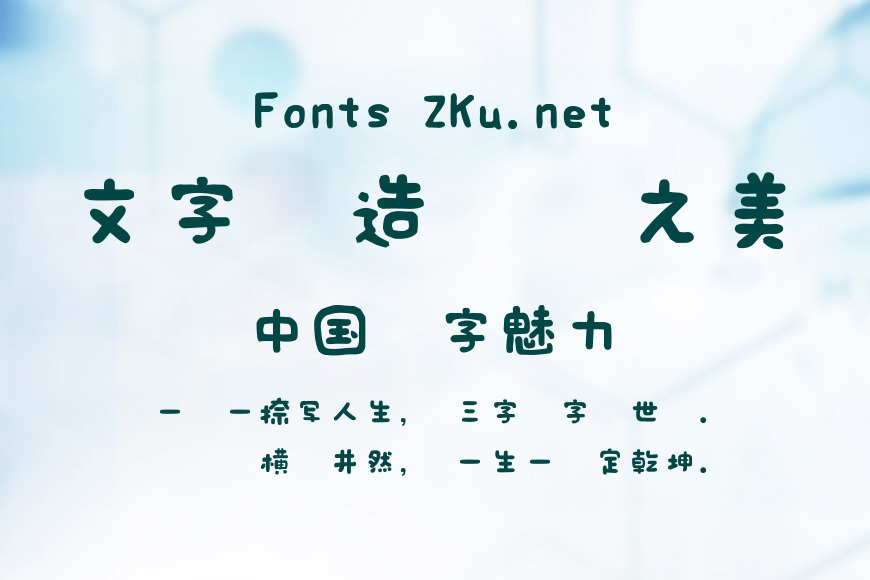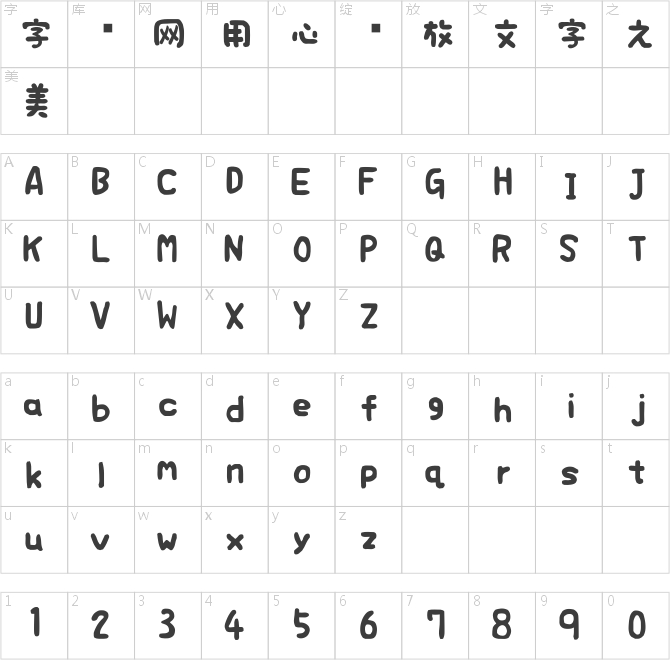
豆豆字体Pえるまー
豆豆字体Pえるまー字体下载Elmer_P Font
えるまーフォント<等幅> ver.1.60
えるまーPフォント<プロポーショナル> ver1.60
マジックペンで書いたような手書きフォントです。<第二水準まで>
足跡やハート等が罫線の後半に入っています。「けいせん」を変換させてみてください。
豆豆字体Pえるまー字体Elmer_P Font字库是一款让人赏心悦目、百看不厌的日文字体,适合各类广告和产品包装设计应用,字体大小3.26MB,格式为ttf字体,上传用户是Apple,作者/版权方为隠れ家